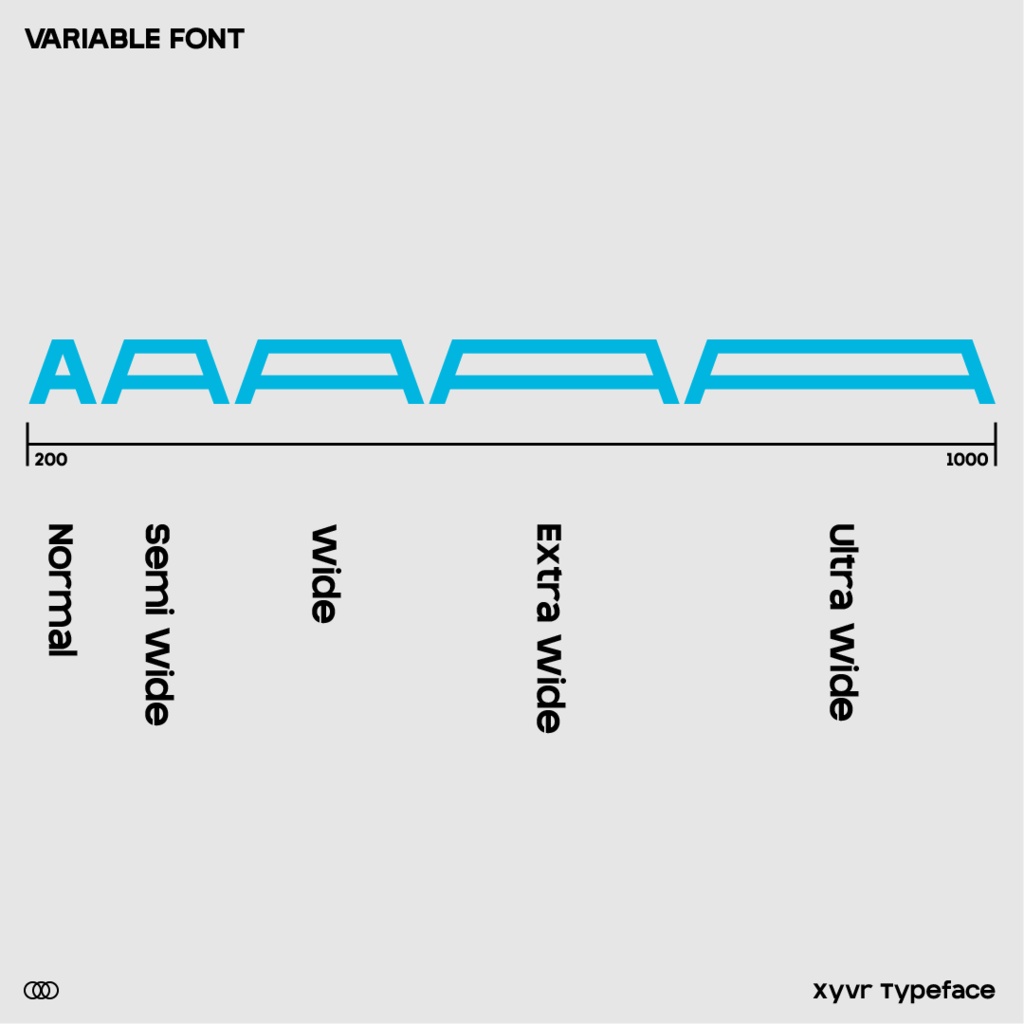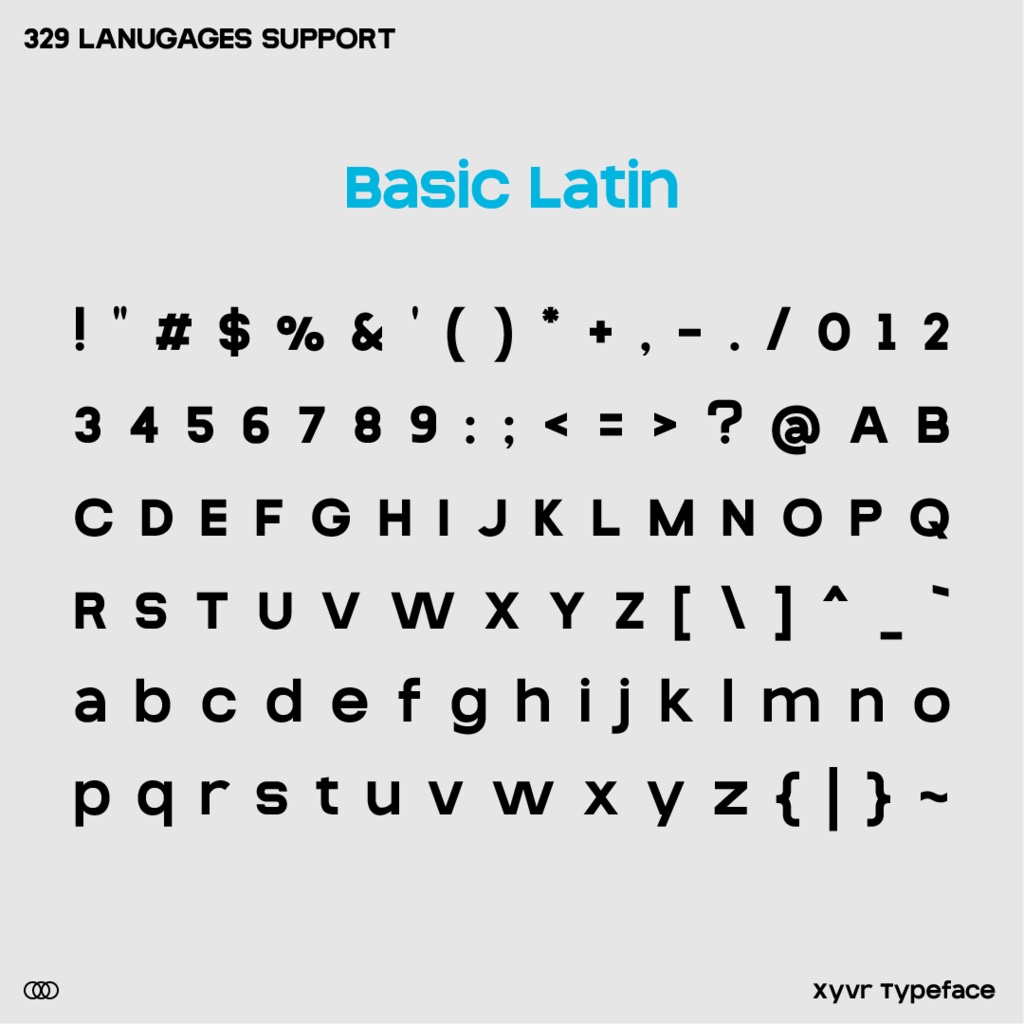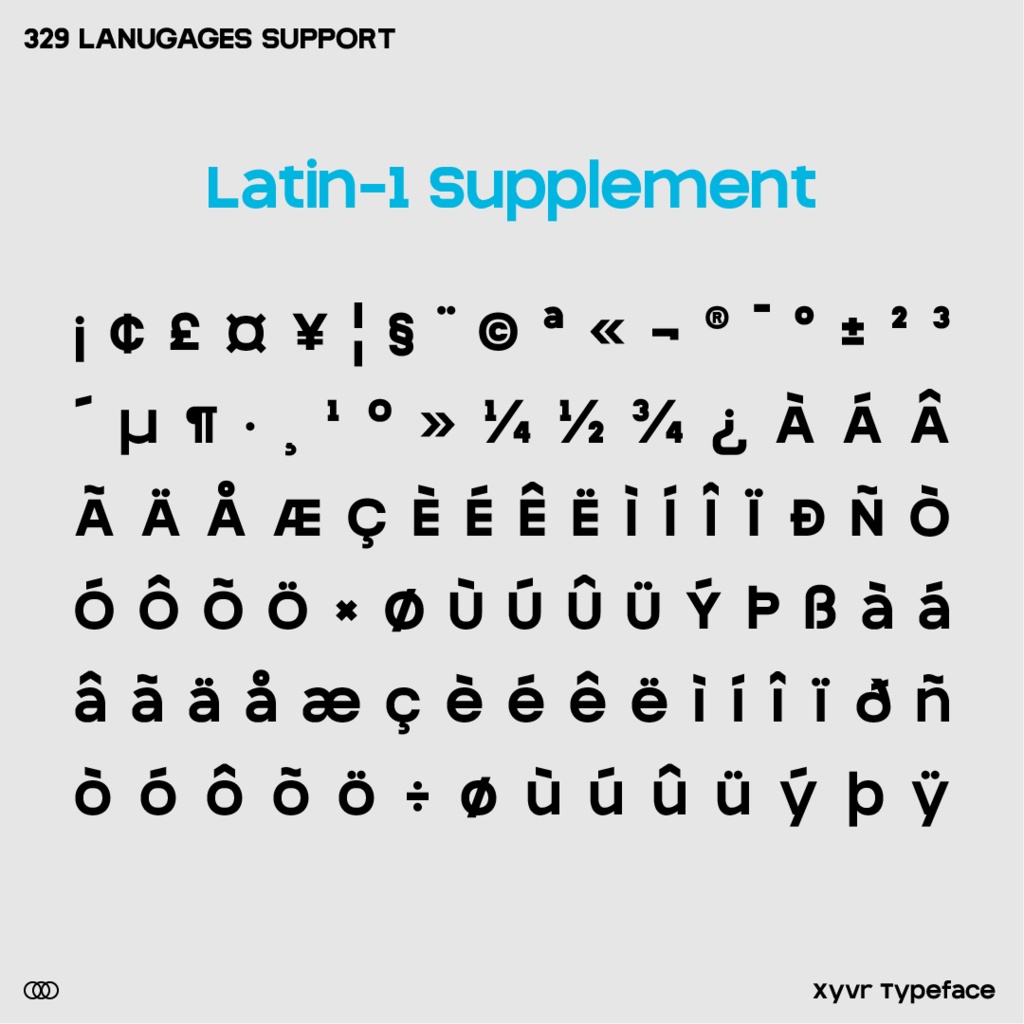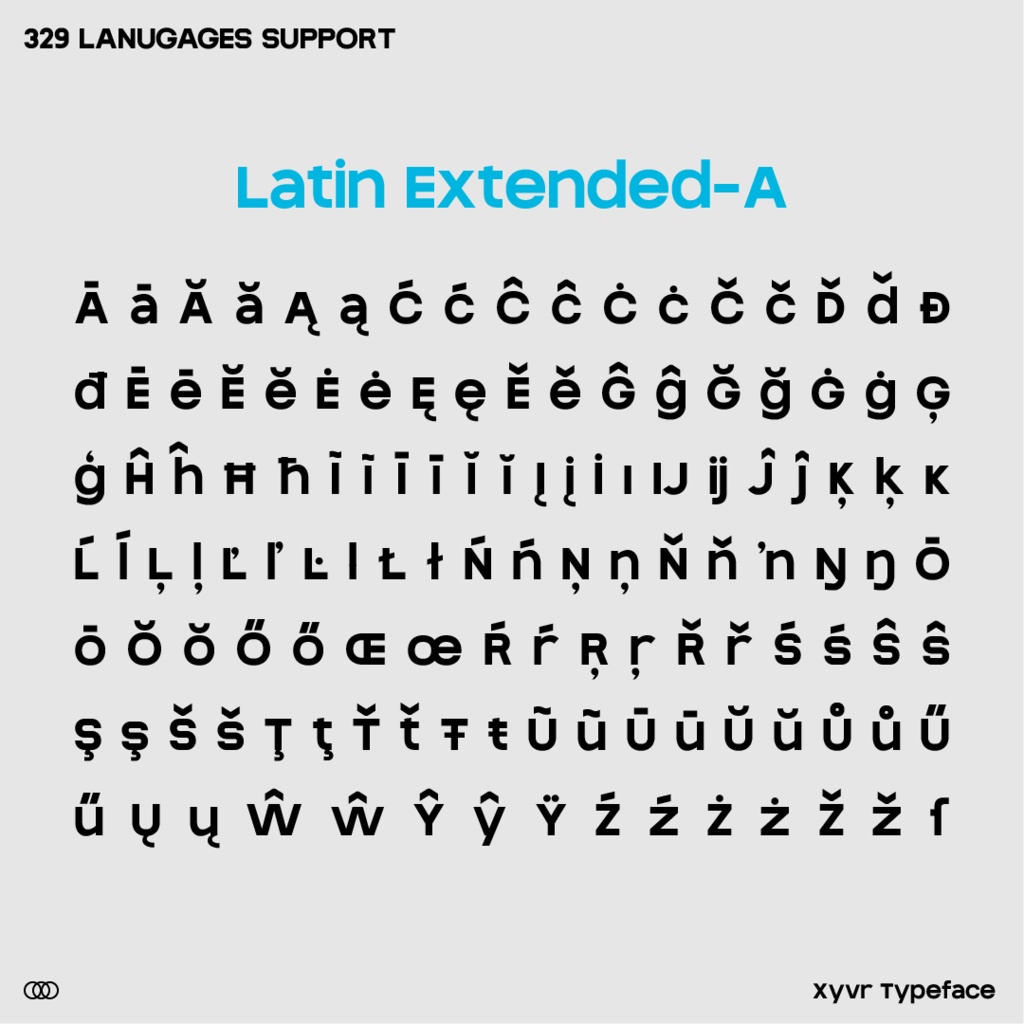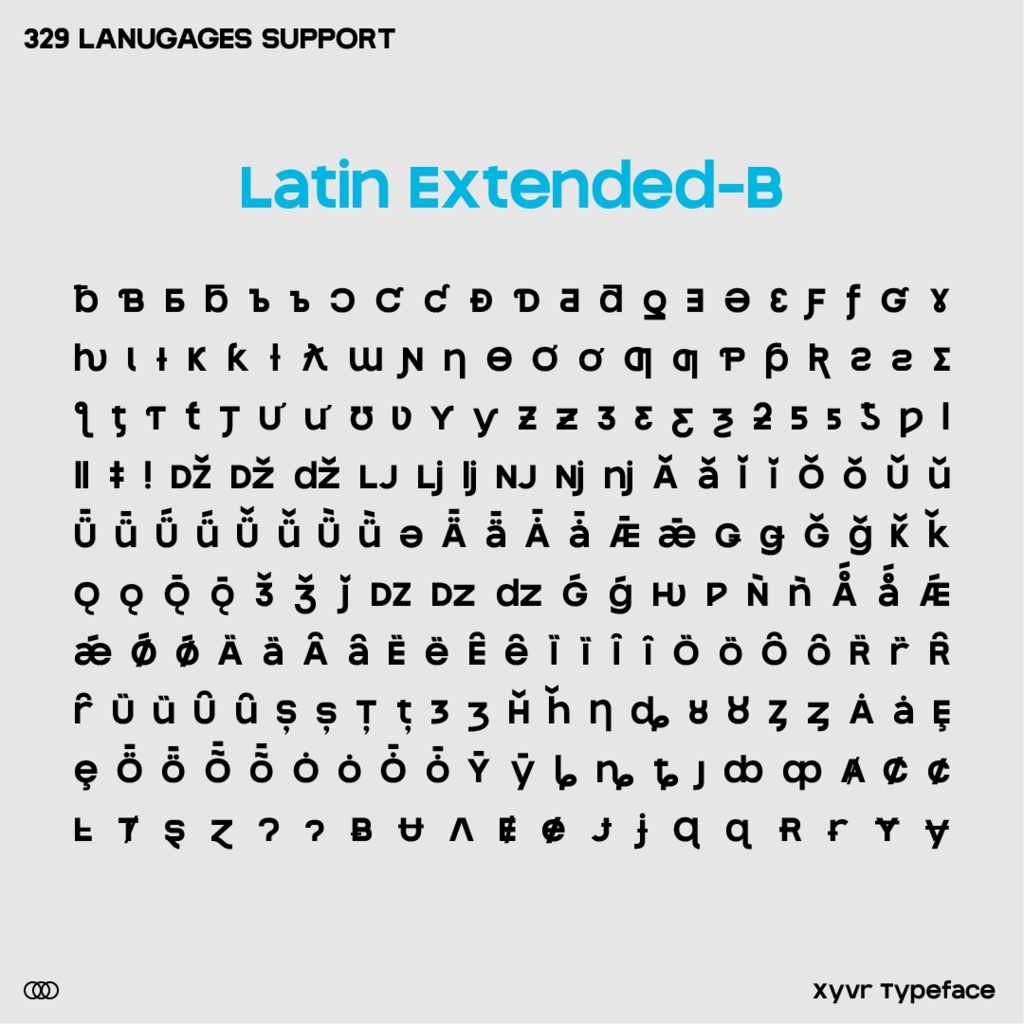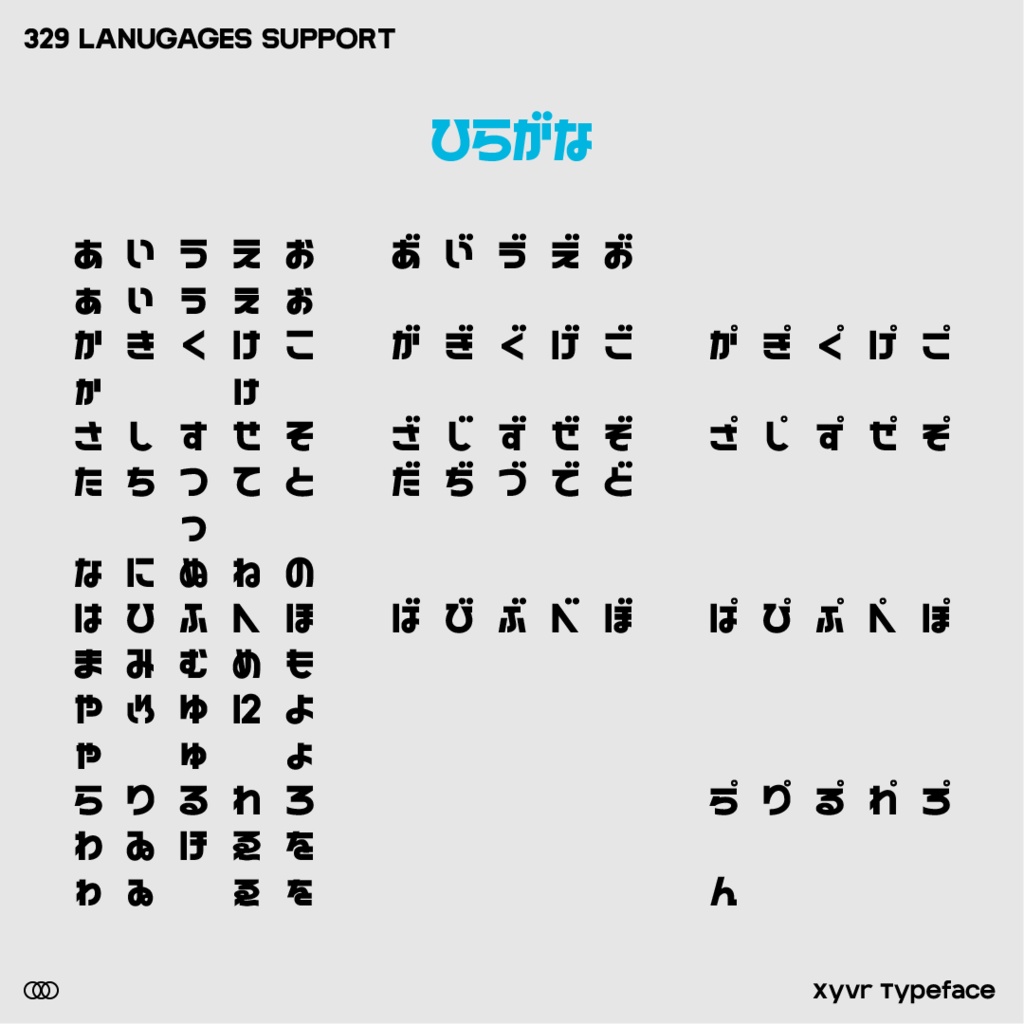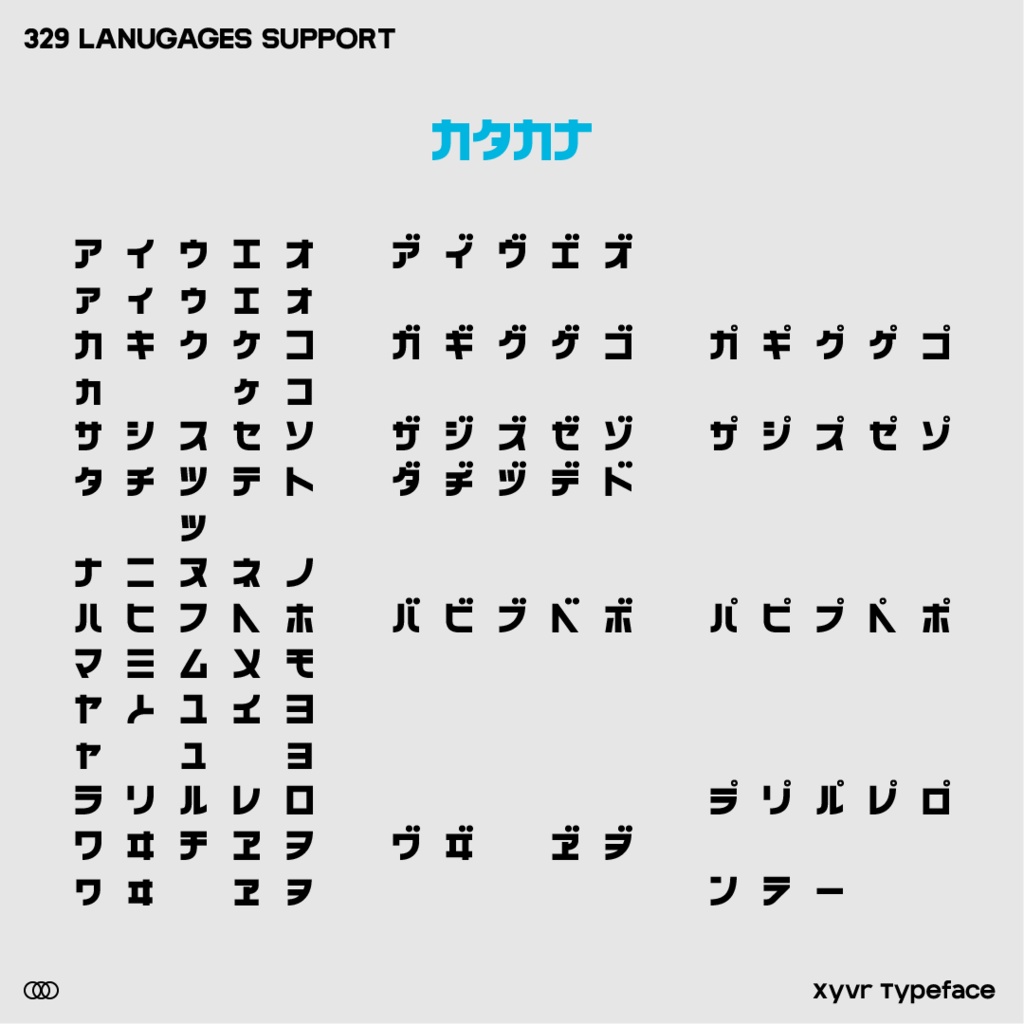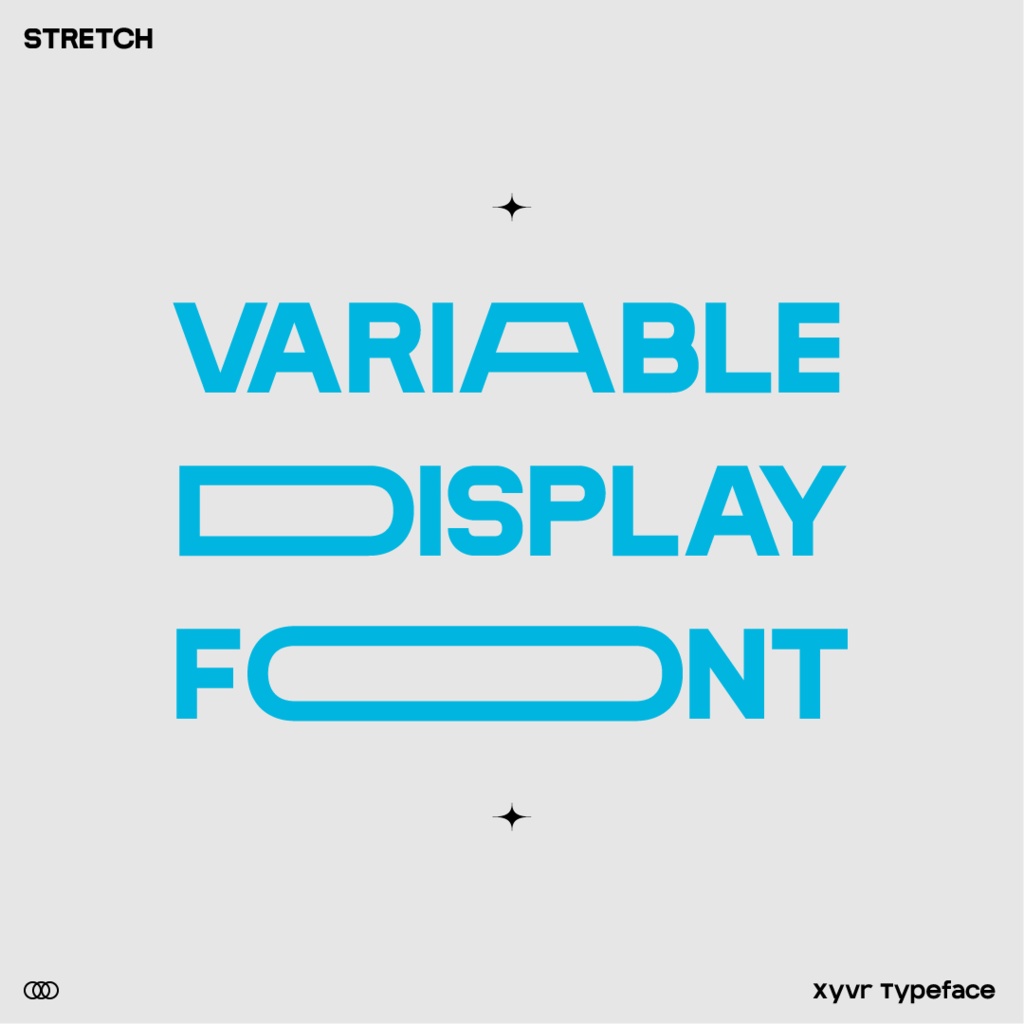
Xyvr【バリアブルフォント】
横にとにかく伸ばせるバリアブルのフォントです。 今後ウェイト軸追加及び漢字対応予定です。 【フォント仕様】 ・収録文字種 基本ラテン文字/ラテン1補助/ラテン文字拡張A/ラテン文字拡張B/ひらがな/カタカナ/その他記号等/一部リガチャ 1,188グリフ/1,073文字 収録 TrueTypeフォント (バリアブル) ●バリアブルフォントについて バリアブルフォントは、対応しているアプリケーションにて完全に動作します。 対応していないアプリケーションでは5段階で幅を変更できるなど制限があるか、使用できない可能性があります。 【利用規約】 当フォントをご利用された時点で、この利用規約に同意したものと見做します。 当フォントデータは、本規約に定める条件でご利用者様に使用する権利を許諾します。 当フォントの著作権やその他一切の権利はPalfに帰属します。 ●使用条件 1) 2人以上の複数人でご利用になる場合のみ、1ライセンスにつき端末3台までといたします。 2) 本フォントを使用して得られる結果については、仕様者自身が責任を負うものとします。 3) 一般印刷物の作成(ポスター、書籍、フライヤー等)にご利用いただけます。 4) 立体制作物の作成(ステッカー、Tシャツ、アクリルキーホルダー等)にご利用いただけます。 5) 映像及びWebに関連する制作物に於いては、画像化・アウトライン化した上でご利用いただけます。 6) ロゴマーク、タイトルデザインの作成にご利用いただけます。 7) 画像化・アウトライン化したものを加工・変形してご利用いただけます。 8) 購入者本人又は事務所内等での限定した使用に限り、当フォントファイルを改変し、本人のみが使用することができます。 ●禁止事項 当フォントファイルを使用する際、以下の事項を禁じます。 1) 第三者への譲渡・貸与・配布・販売 2) 当フォントデータを元とした、類似又は同一フォントのデータの作成 3) 公序良俗に反する目的、誹謗中傷目的での使用 4) 政治的・宗教的利用 5) 犯罪への利用 6) 当フォントデータのサーバー上へのアップロード 7) 当フォントデータを取り出すことができるソフトウェアへの組み込み ●その他 ・上記に記載されていない事項については、著作権法及び関連法規に従うものとします。 ・本利用規約は予告なしに変更されることがあります。